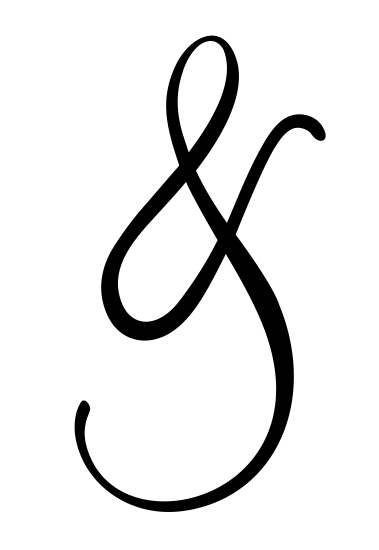
woher der ampersand?
habe dieses &-zeichen in einem fremdlogo drin, das ich zu bearbeiten habe.
die strichstärken sind allerdings leicht modifiziert. bevor ich jetzt anfange, in den pfaden rumzupfuschen nehm ich vielleicht doch lieber das original-zeichen. nur aus welchem font isses? ich komm nicht dahinter, obwohl es mir verdammt bekannt vorkommt.
das rennen ist eröffnet!
ähnlich:
(Warum auch immer das & als Specimen nicht angezeigt wird …)
Die Berthold-Script ist noch näher dran.